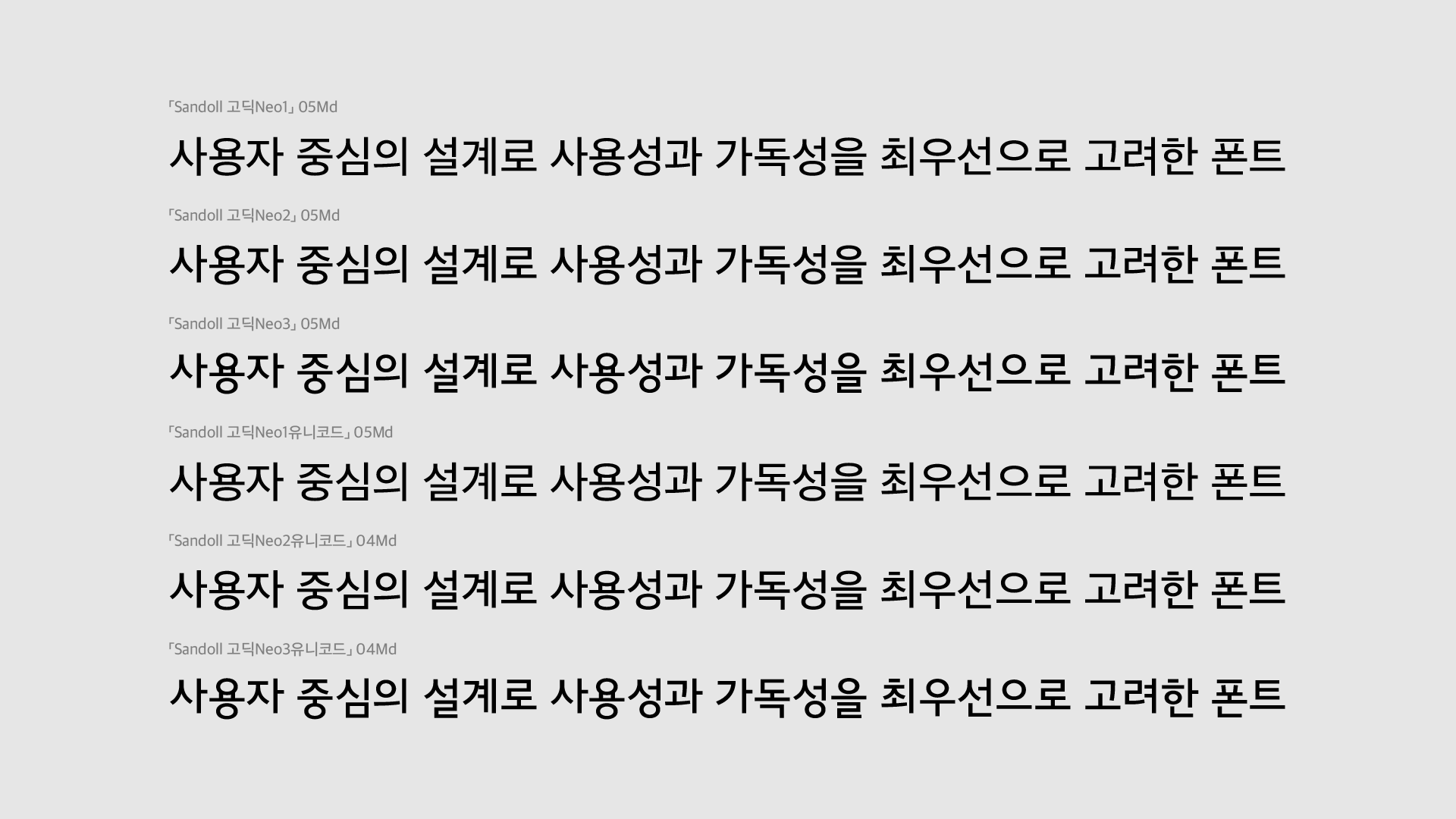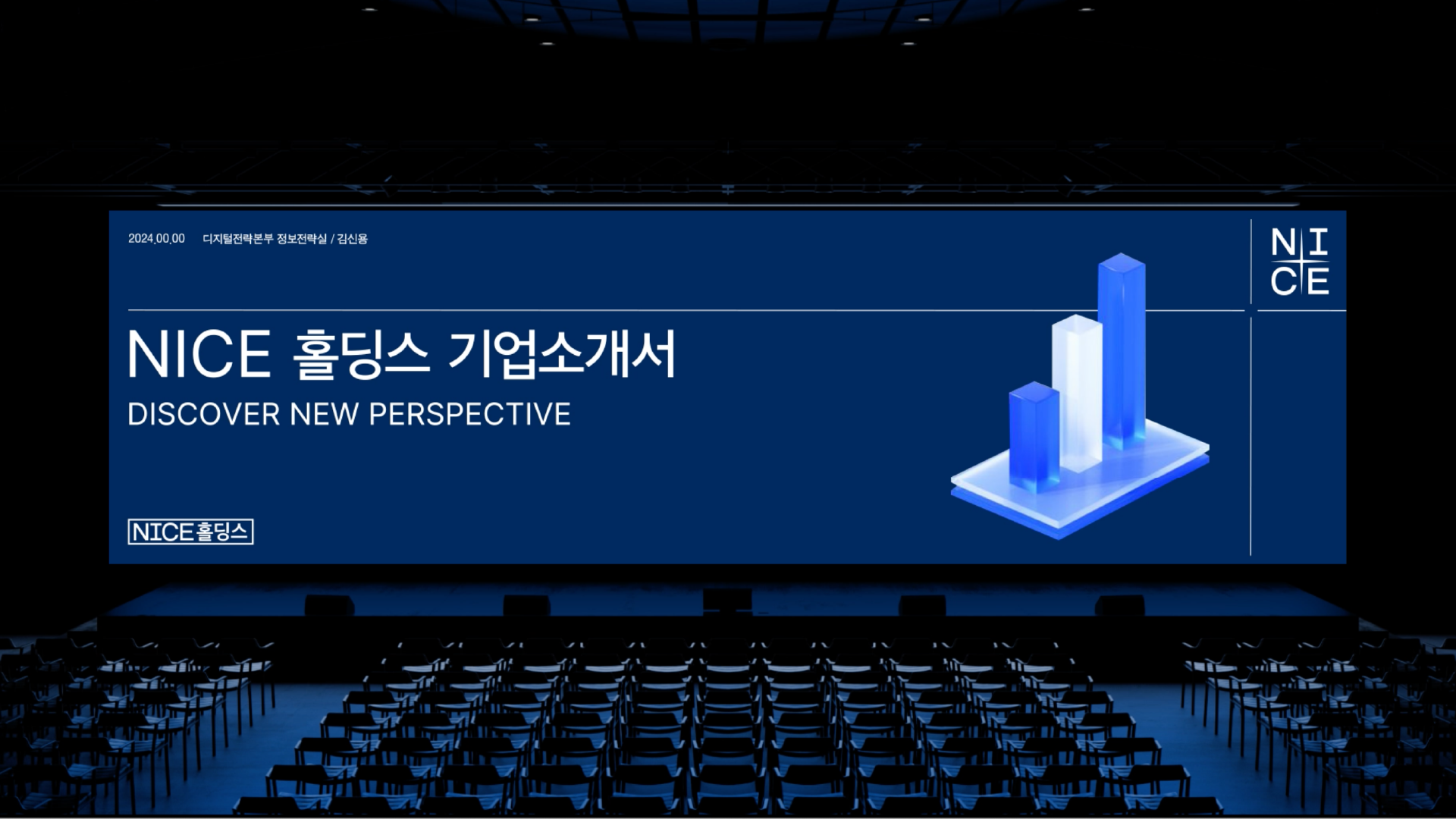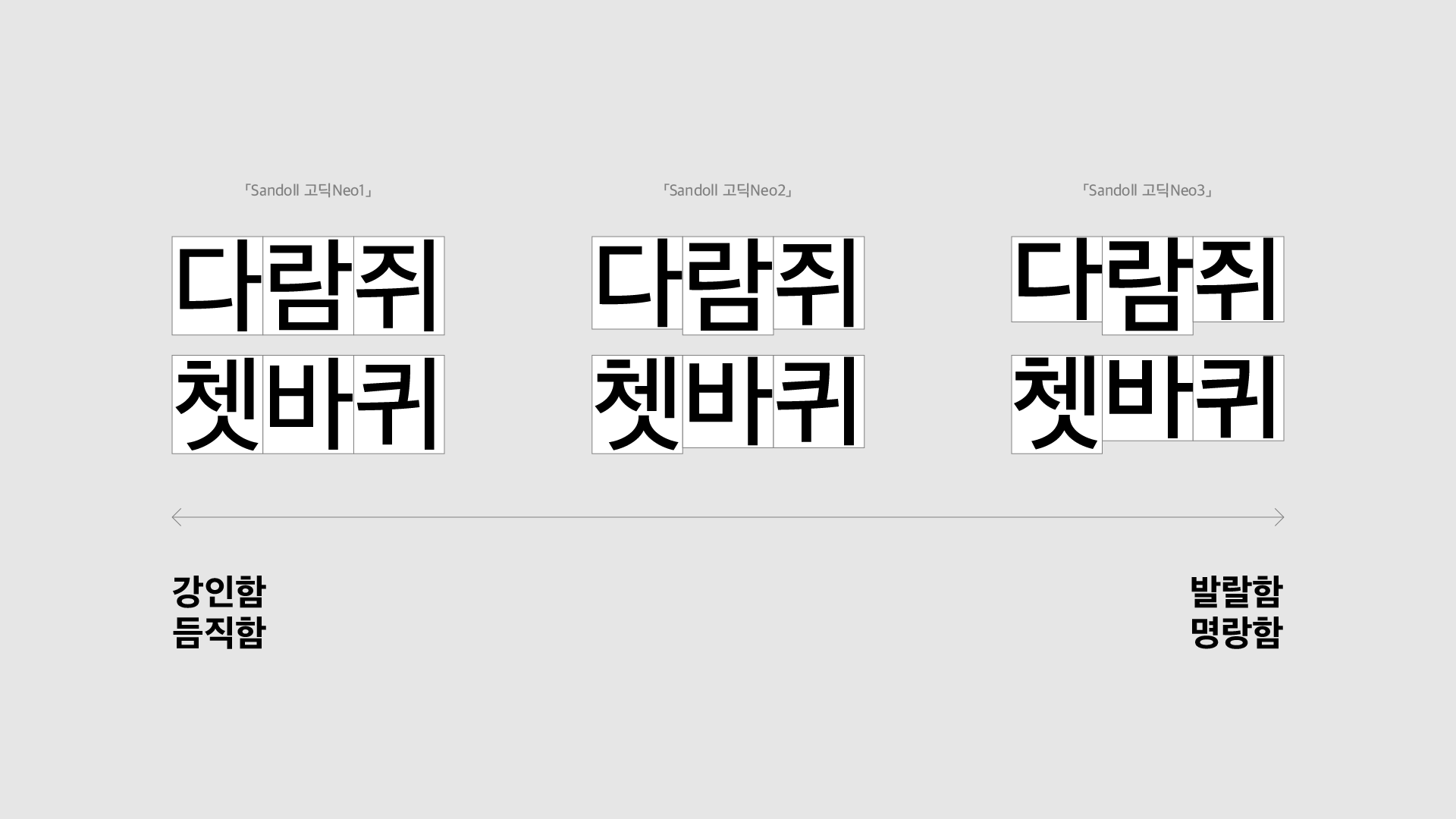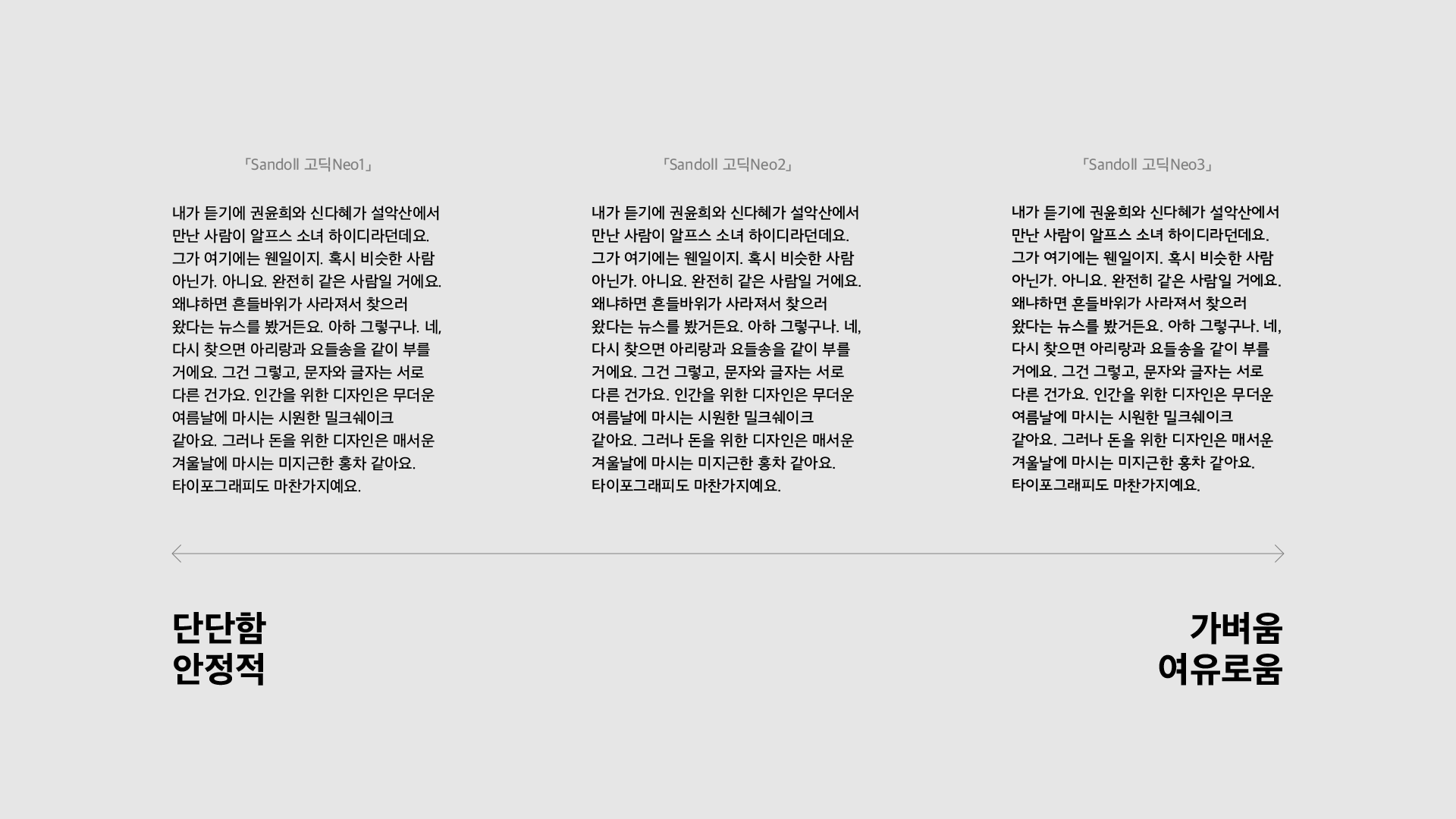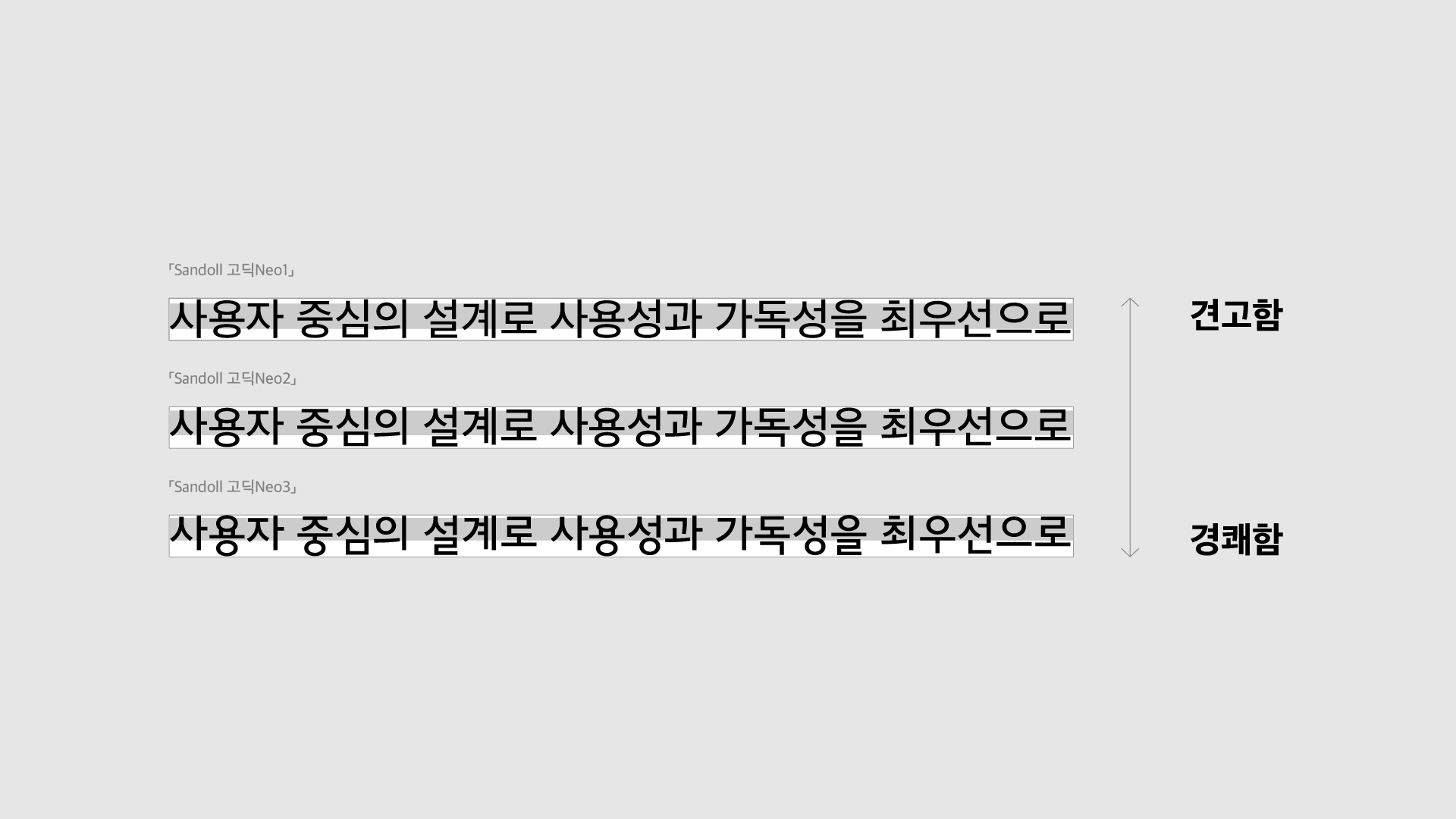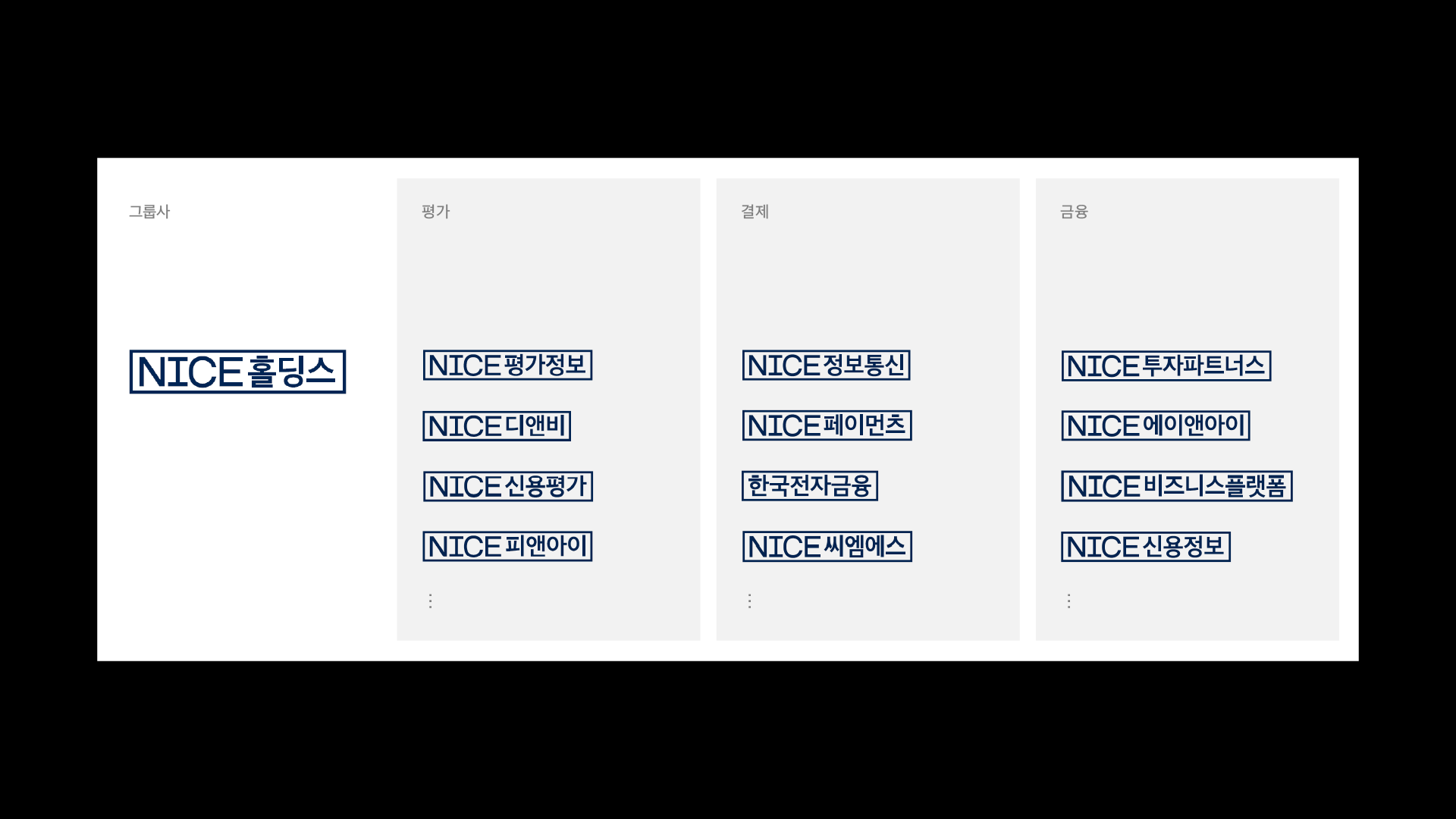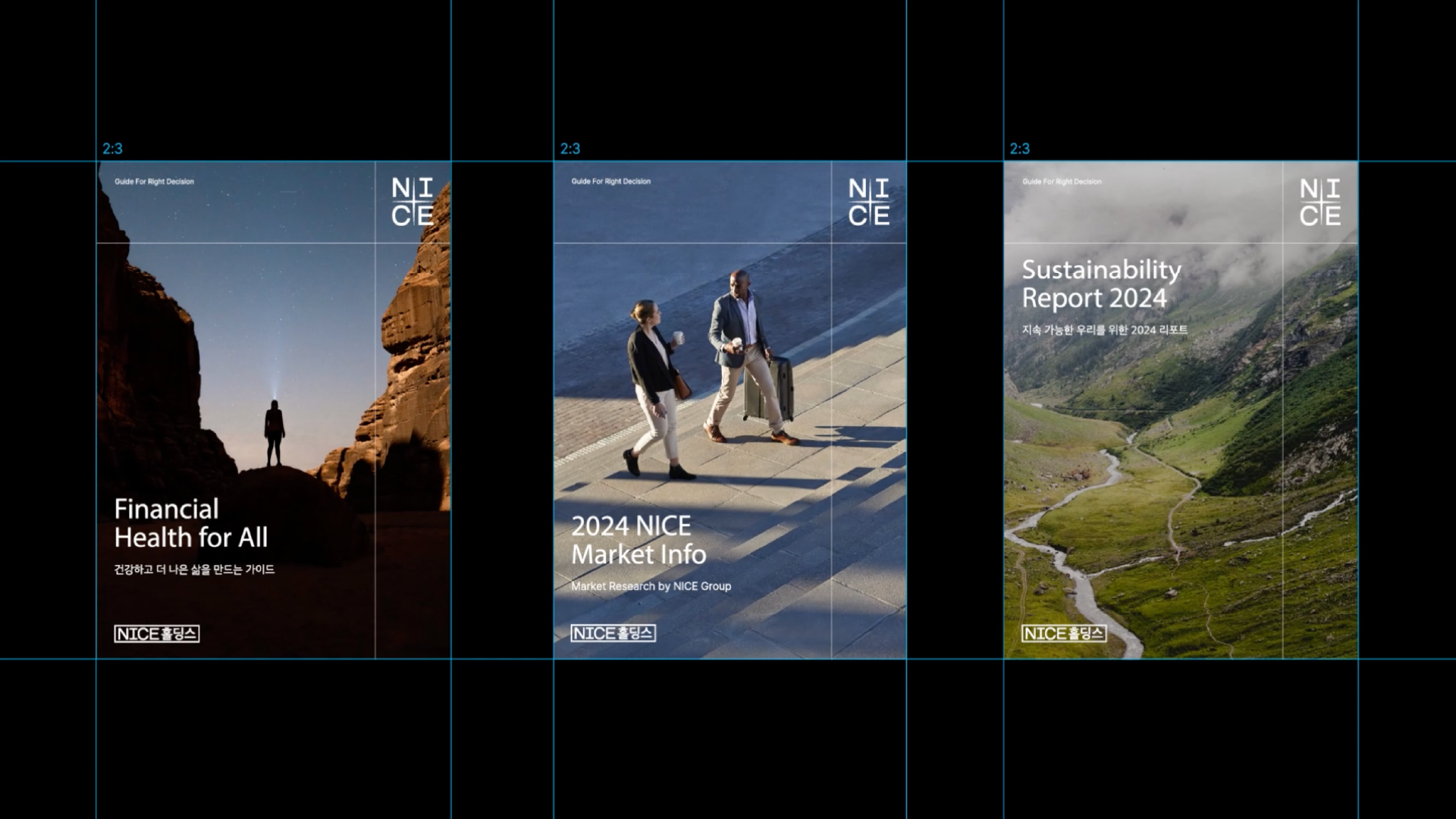
[타입브랜딩]지정폰트: 브랜드의 표정
전용폰트? 지정폰트?
일관된 시각 경험을 위해 많은 기업과 브랜드에서 폰트를 활용해요. 내부 문서에도, 이벤트 안내 게시글에도 폰트는 언제나 포함되어 있죠. 브랜드의 다양한 접점에서 폰트는 빠질 수 없기 때문에 브랜드 정체성 구축에 중요한 역할을 해요. 그만큼 브랜드의 폰트는 신중히 고민하고 적용해야 하는데요. 헷갈리는 개념인 전용폰트와 지정폰트에 대해서 짧게 설명 드릴게요.
전용폰트(전용서체)는 브랜드를 위해 특별히 제작된 폰트로 브랜드의 고유성을 텍스트에 담아내 CI, BI가 없어도 브랜드를 인지시킬 수 있는 효과가 있어요. 때문에 전용폰트는 다른 브랜드와의 차별화를 돕고 일관성 있는 시각적 아이덴티티를 글자에서도 보여 줄 수 있어요. 하지만 전용폰트 개발은 비용과 시간을 필요로하기 때문에, 모든 브랜드가 전용폰트를 보유하고 있진 않아요. 이런 경우에는 지정폰트(지정서체)를 사용하기도 해요. 지정폰트는 그 브랜드만을 위해서 만들어진 고유한 폰트는 아니지만 특정 폰트를 지정해 브랜드 매체 전체에 일관되게 적용하는 폰트예요.
『Sandoll 고딕Neo』 시리즈
많은 브랜드에 사랑받는 폰트인 『Sandoll 고딕Neo』 시리즈 중 「Sandoll 고딕Neo1」은 정식 출시 전부터 Apple, LG, Pantech 등 글로벌 기업의 시스템 폰트로 사용됐어요. 「Sandoll 고딕Neo1」 2011년 출시됐지만, 유니코드* 확장, 힌팅** 적용 등 지속적으로 고도화하고 있는 완성도 높은 폰트인데요. 산돌은 「Sandoll 고딕Neo2」, 「Sandoll 고딕Neo3」를 추가로 개발해 지정폰트의 선택지를 넓혔어요. 선택지가 넓어진 만큼 디자이너들이 지정폰트를 고르는 데 신중해졌을 거예요. 나의 브랜드 이미지와 잘 어울리는 폰트를 고를 수 있도록 『Sandoll 고딕Neo』 시리즈의 ‘인상’에 대해 이야기해 볼게요.
*유니코드: 국제 표준 문자 시스템을 ‘유니코드(링크)’라고 해요. 「Sandoll 고딕Neo1 유니코드」는 「Sandoll 고딕Neo1」을 개선하고 기존 2,350자에 8,822자를 더해 11,172자를 제공하고 있어요.
**힌팅: 폰트가 작은 크기로 표시될 때도 선명하게 보이도록 글자의 벡터 데이터를 디지털 화면의 픽셀 격자에 맞추는 것을 뜻해요. 낮은 해상도의 화면에서도 왜곡되어 보이지 않도록 다양한 디스플레이 환경에 최적화하는 기술이에요.
폰트가 짓는 표정
낱글자가 네모꼴에 가까울수록 리듬감이 적고 탈네모꼴일수록 리듬감이 강해지기 때문에 네모꼴은 견고하고 듬직한 인상이 느껴지고 탈네모꼴은 발랄하고 명랑한 인상을 띄어요.
이 기준에 따라서 『Sandoll 고딕Neo』를 살펴보면 「Sandoll 고딕Neo1」에서 「Sandoll 고딕Neo3」로 갈수록 탈네모꼴에 가까워져 율동감의 차이를 확인 할 수 있는데요. 숫자가 높을수록 더 인상이 명랑해지는 것이 느껴지시나요? 친근하고 발랄한 인상으로 브랜드를 포지셔닝 했다면 이에 맞춰 지정폰트도 「Sandoll 고딕Neo3」를 선택할 수 있어요. 신뢰가 느껴지는 인상이 좋다면 네모꼴에 가깝고 안정적인 「Sandoll 고딕Neo1」을 선택해 주는 것이 좋겠죠. 듬직함이 느껴지면서도 친절한 브랜드 이미지를 추구한다면 「Sandoll 고딕Neo2」를 지정폰트로 사용할 수도 있어요.
글줄의 흐름과 글자 중심선으로도 폰트의 인상을 파악할 수 있는데요. 「Sandoll 고딕Neo1」처럼 글자 중심선이 낮을수록 견고한 인상이, 「Sandoll 고딕Neo3」처럼 글자 중심선이 높을수록 경쾌한 인상이 형성돼요.
글자 사이 공간과 회색도에서도 인상을 확인할 수 있어요. 결구에 따라 낱글자를 둘러싼 공간이 형성되는데, 긴 글로 조판 된 글줄에서 더 도드라지게 나타나요. 이런 요소들에 의해서 단단하거나 가벼운 인상이 표현되기도 해요.
나이스그룹의 새로운 인상, 「Sandoll 고딕Neo2」
나이스홀딩스는 국내 최대 금융 인프라 기업으로 신용평가, 신용정보, 자산관리 등 국내 자본 시장의 기준을 만들어가는 기업이에요. 최근 나이스홀딩스는 대대적으로 CI 시스템을 개편했는데요. 이 과정에서 「Sandoll 고딕Neo2」를 그룹사 지정폰트로 적용했어요. 「Sandoll 고딕Neo3」 보다 안정적인 글줄과, 「Sandoll 고딕Neo1」보다 곡률이 크게 작도 된 「Sandoll 고딕Neo2」는 신뢰가 느껴지면서도 새롭고 창의적인 인상을 주기도 해요. 아래는 나이스그룹의 변경된 계열사 CI인데요. 신뢰와 혁신의 이미지가 잘 느껴지는 것 같아요.
‘브랜드다움’을 보여주는 도구
브랜드의 모든 접점에 디자이너가 관여한다면 좋겠지만, 현실적으로는 어렵기 때문에 지정폰트가 필수적이에요. 작업자가 여럿이거나 디자이너가 아닌 이가 작업 해야 하는 환경에서 폰트를 통해서 브랜드의 시각적 통일성을 유지할 수 있어요. 예를 들어, 계약서나 인보이스는 디자이너보다 재무팀, 법무팀, 세일즈팀에 더 익숙한 매체죠. 이렇게 다양한 문서에서 브랜드의 시각 정체성을 유지하기 위한 도구로 폰트를 사용할 수 있어요.